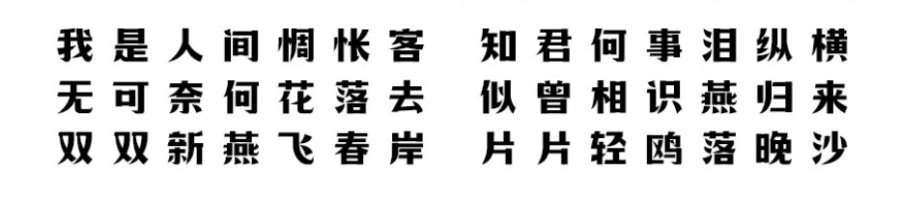
宋体的特点是字形方正、笔画横平竖直、横细竖粗、棱角分明、结构严谨、整齐均匀、有极强的笔画规律性,能够使人在阅读时有一种舒适醒目的感觉。但是单一的宋体目前已经满足不了设计师们的日常使用需求了,字库公司开始设计一些和宋体相似但又不太一样的宋体,我们暂时称呼其为创意宋体。
创意宋体保留了宋体的一部分特征,但是对大部分笔画进行了重新设计。如:上首国宋体。体笔画采用较为接近宋体做法,但笔画整体更加大气,直线与曲线交汇,特点是横笔呈直角梯形,笔画整体粗细均匀,字体柔美稳重但又不失大气浑厚,整体给人一种稳重踏实的感觉。